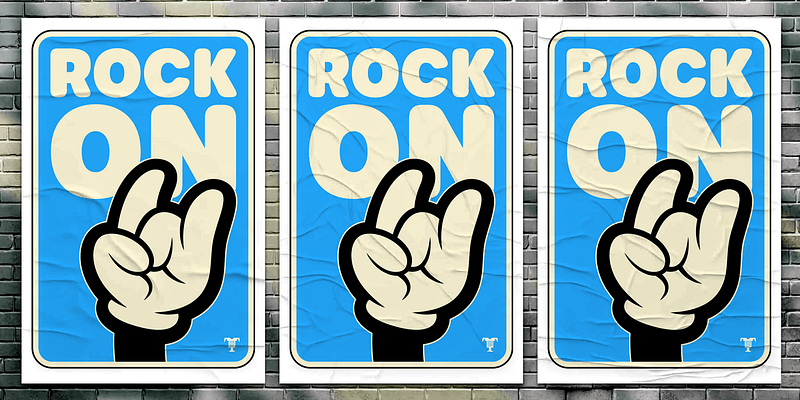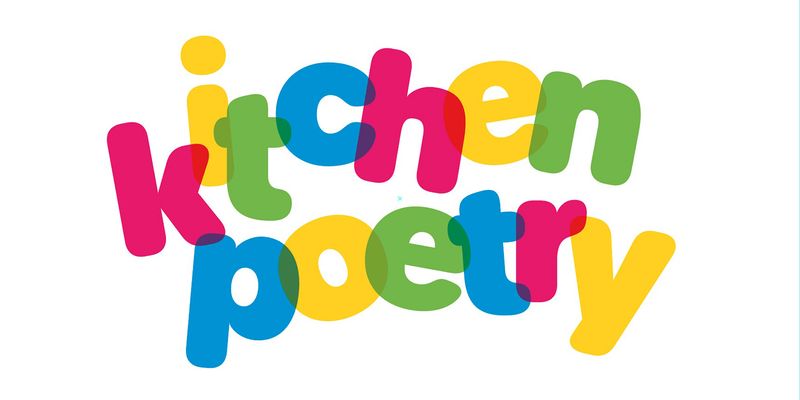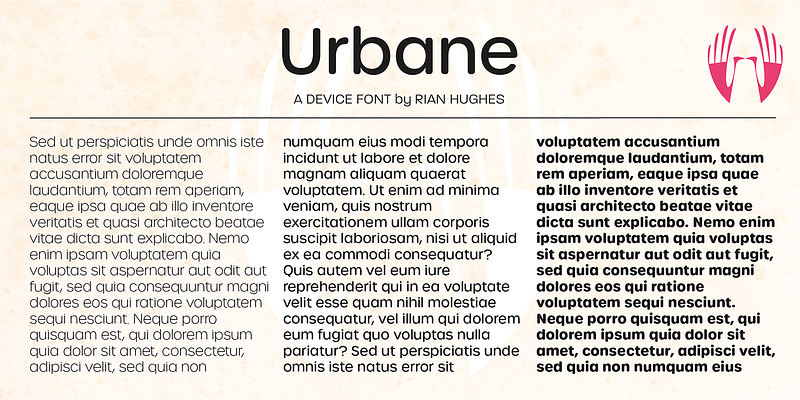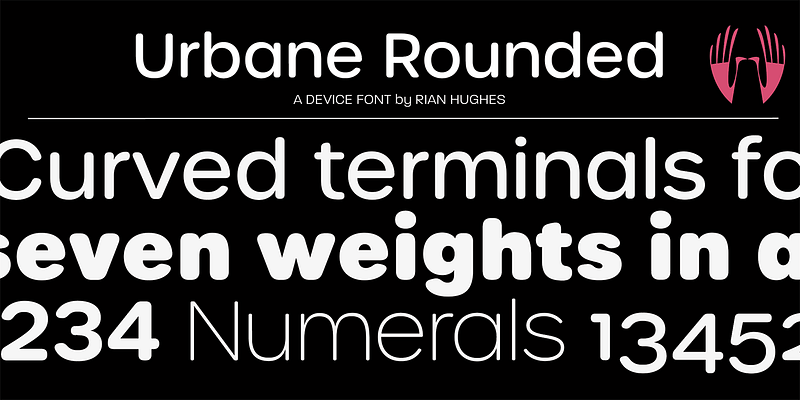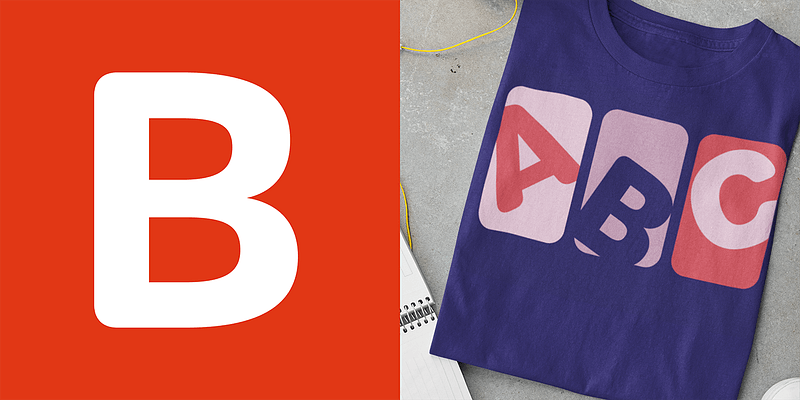
Bourreau de travail polyvalent, cette famille propose une vaste application. La plus grande hauteur d’œil donne une lisibilité accessible même dans les petites tailles, tandis que la gamme de graisses et de styles (italique, script, arrondi, rugueux) forme une grande famille polyvalente.
Typographie, conception et imagerie par l’illustrateur et typographe anglais Rian Hughes.